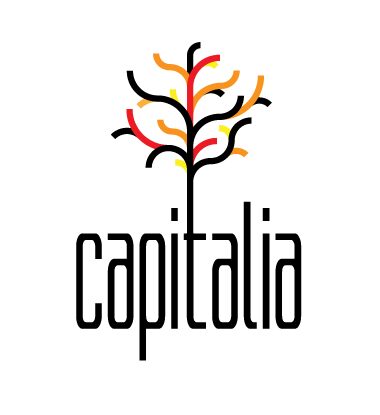
Capitalia Rounded autorstwa Tobiasa Sommera to darmowy, wąski, jednokreskowy krój pismowy typu display o wysokich, ściśle wykreślonych literach. Jego linie zachowują równą grubość, a kanciasta struktura została złagodzona zaokrąglonymi rogatymi połączeniami i wygiętymi łukami. Długie pionowe linie tworzą uderzający profil przypominający panoramę miasta.
Architektura i motywy miejskie naturalnie pasują do jego wąskich, strukturalnych form. Liternictwo może nadać kształt plakatom, grafikom okolicznościowym i oprawie muzycznej w czystym, lecz niekonwencjonalnym stylu. Jest szczególnie polecane odbiorcom zorientowanym na design, którzy cenią modernistyczną geometrię i liternictwo o bardziej skonstruowanym niż neutralnym charakterze.